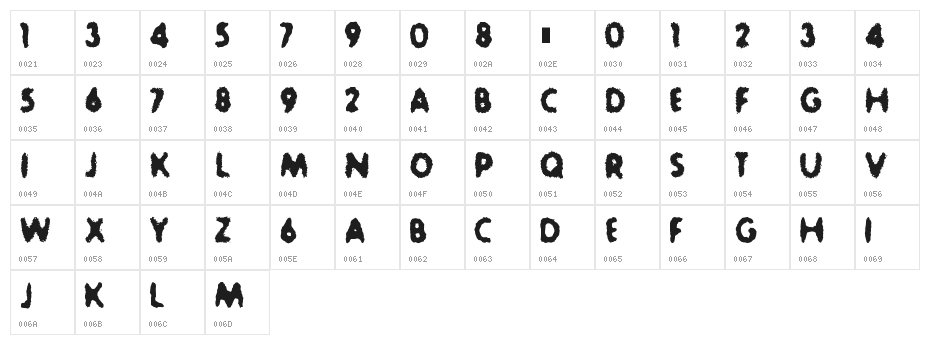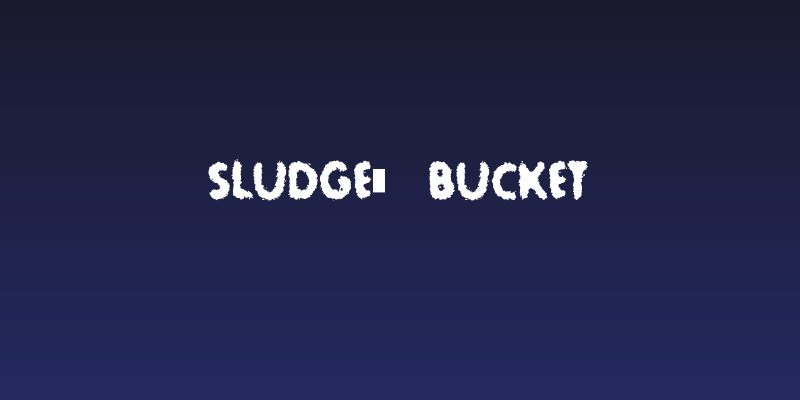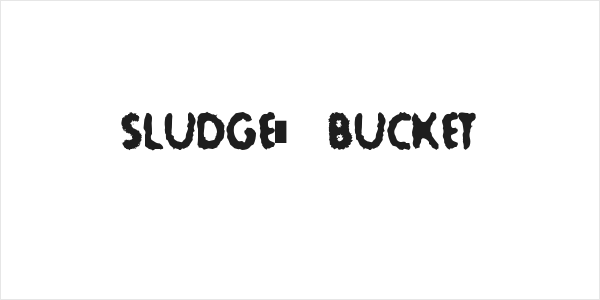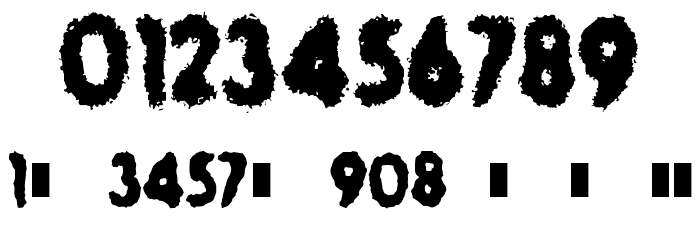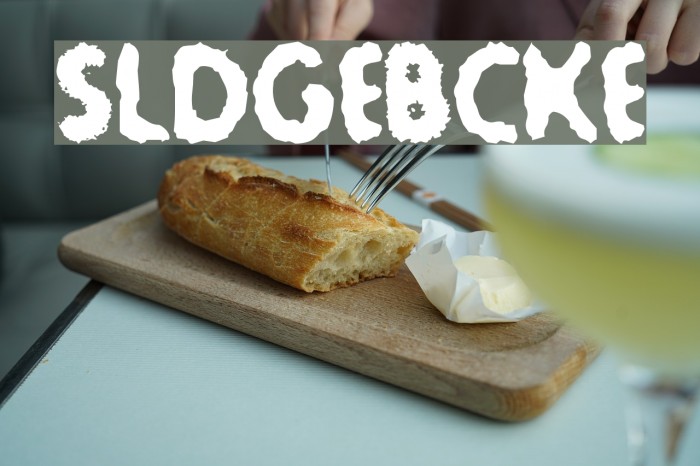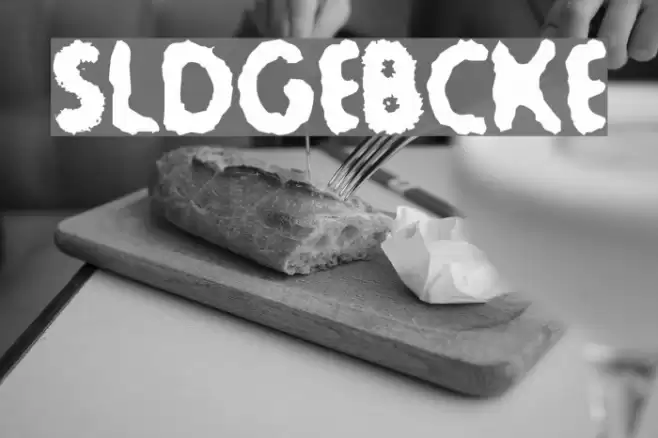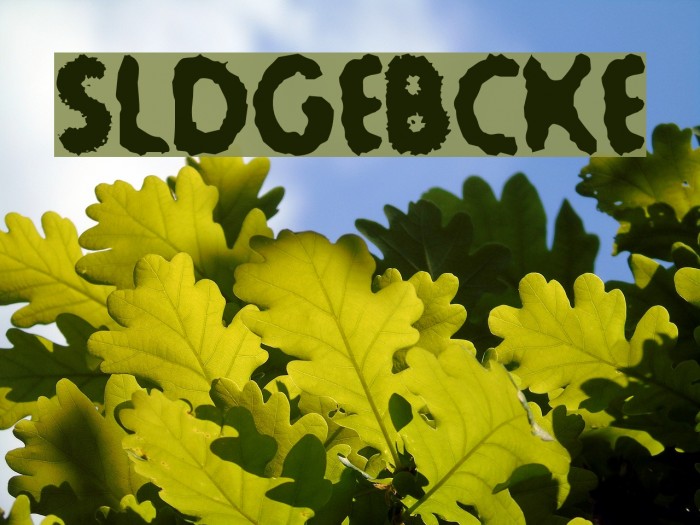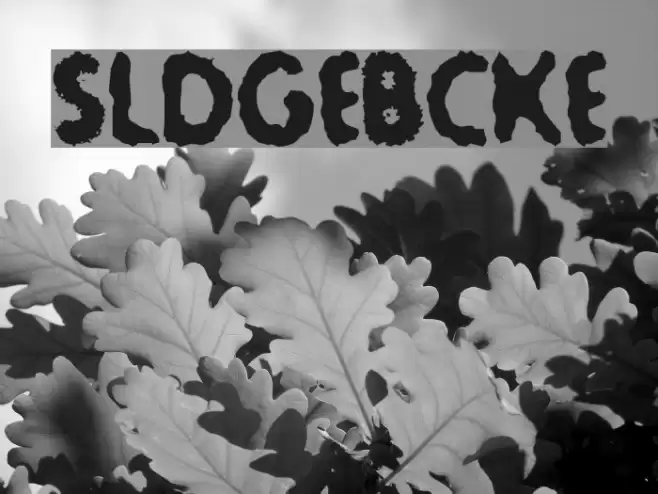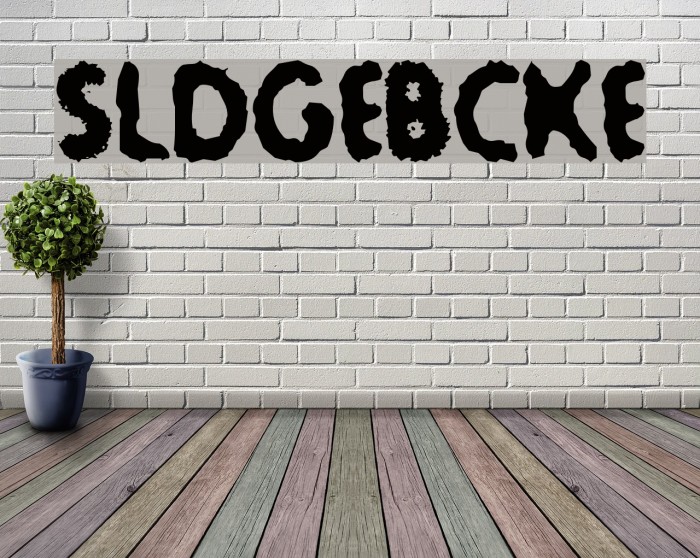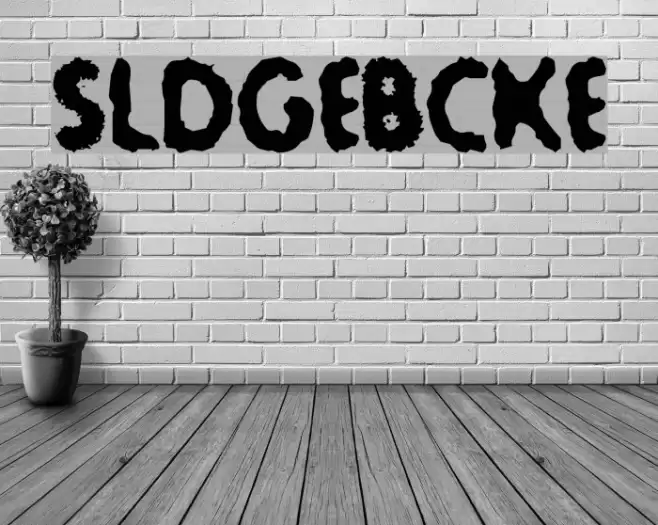
Sludge-Bucket Font
✎ Distorted Eroded
| Proiecte propuse | Ideal for horror-themed designs, edgy posters, album covers, and any project requiring a dramatic, eye-catching typeface. |